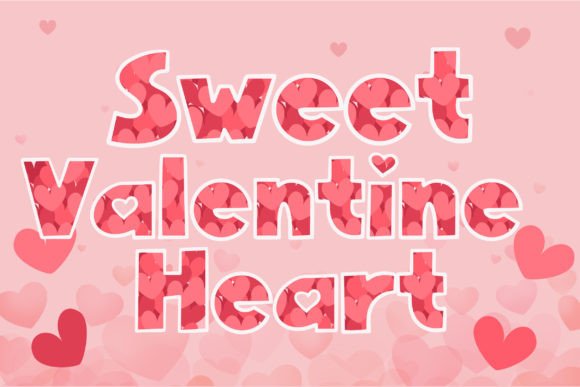
Sweet Valentine Heart
適切なデザイン要素を見つけるのは難しい場合がありますが、Sweet Valentine Heartは作品を即座に引き立てる優れたコレクションを提供します。
POD(オンデマンド印刷)製品、結婚式の招待状、またはソーシャルメディアのグラフィックを作成している場合でも、Sweet Valentine Heartは理想的です。